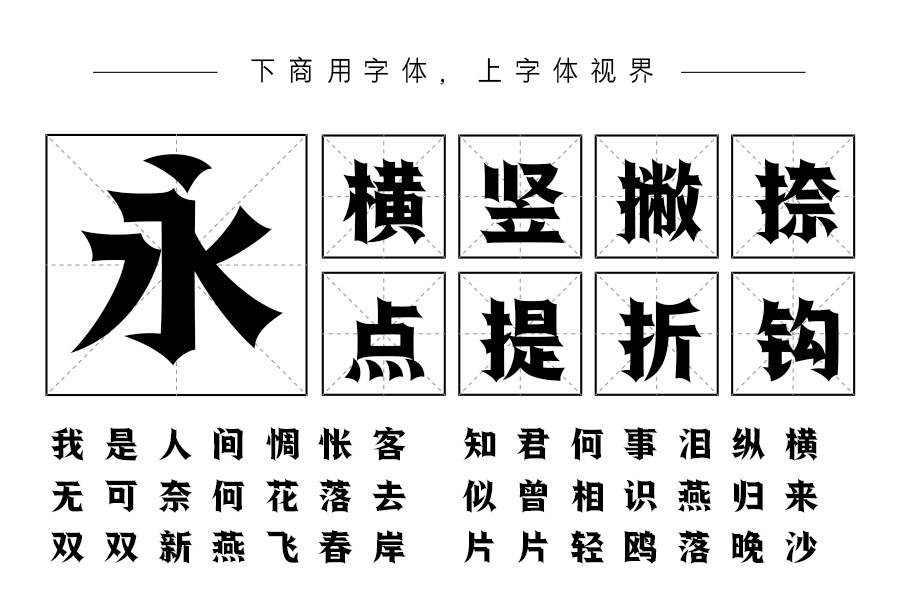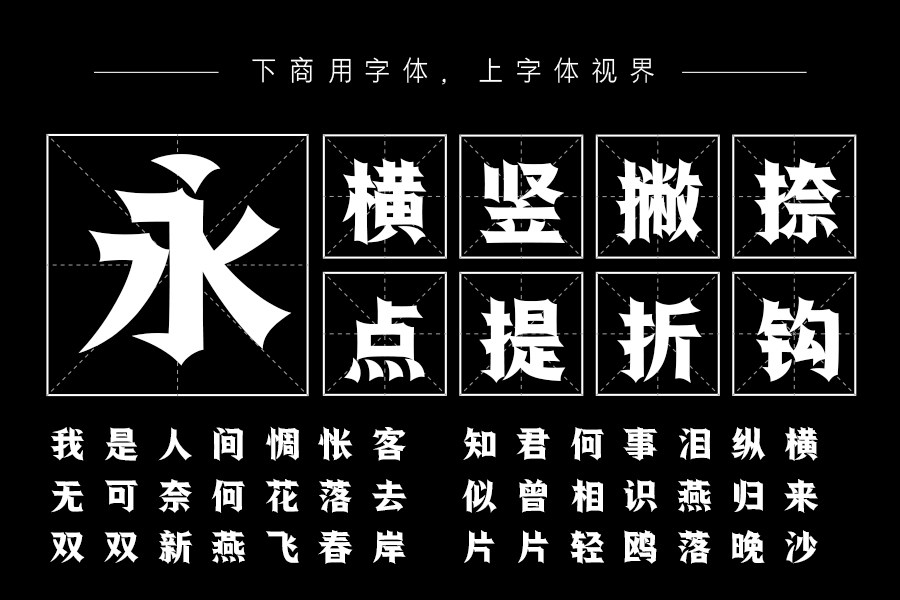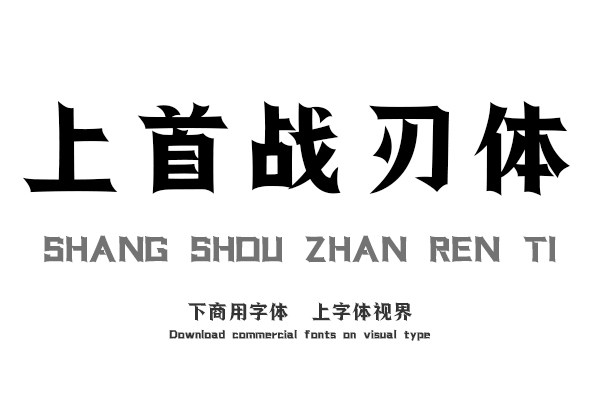
上首战刃体,简体中文约6763字,其字形锋利又富有张力,表现出锋锐又具有厚重的形态。横竖平直厚重,撇捺柔化尖锐,使得文字展现出厚重而又锋锐的武器,握在手中披荆斩......购买须知:“下载服务费”与“字体VIP”所获得字体 仅用于个人非商用, 商用请联系付费授权。本字体为电脑用字,手机没有root权限不支持直接手机换字(手机如何root,请自行百度搜索教程)。购买前请先 了解清楚后再付款 ,字体为虚拟产品无法回收 一旦购买不支持退款。